25 meilleures polices PowerPoint 2023 (gratuites et premium)
Publié: 2023-09-05Êtes-vous un graphiste à la recherche de la police parfaite pour améliorer le design de vos présentations PowerPoint ? Cherchez pas plus loin! Dans cet article de blog, nous partagerons avec vous les 25 meilleures polices PowerPoint qui feront passer vos projets au niveau supérieur.
Mais d’abord, vous vous demandez peut-être pourquoi le choix de la bonne police est-il si important dans la conception PowerPoint ?
Lorsqu’il s’agit de créer des présentations visuellement attrayantes et percutantes, le choix de la police joue un rôle crucial. Cela peut faire ou défaire la conception globale et la lisibilité de vos diapositives.
Saviez-vous que selon une étude du MIT, un mauvais choix de police peut nuire considérablement à la rétention des informations ? D’un autre côté, utiliser la bonne police peut améliorer la compréhension et l’engagement de votre public.
Il ne s’agit donc pas seulement d’esthétique, mais aussi de communication efficace de votre message à vos téléspectateurs.
Maintenant que nous comprenons l'importance de choisir la bonne police pour vos présentations PowerPoint, plongeons-nous dans notre liste des 25 meilleures polices PowerPoint.
Dans cet article, nous explorerons une variété de styles et de caractéristiques de police, d’élégants et sophistiqués à modernes et audacieux.
Alors préparez-vous à découvrir la police parfaite qui élèvera vos présentations PowerPoint vers de nouveaux sommets.
Meilleures polices PowerPoint premium
Vous cherchez à faire passer vos présentations PowerPoint au niveau supérieur ? Ne cherchez pas plus loin, car dans cette section d'article, nous avons sélectionné les meilleures polices PowerPoint premium qui amélioreront instantanément la conception et l'attrait visuel de vos projets.
Alors pourquoi attendre ? Plongez et découvrez la police parfaite pour votre prochaine présentation.
Anisver
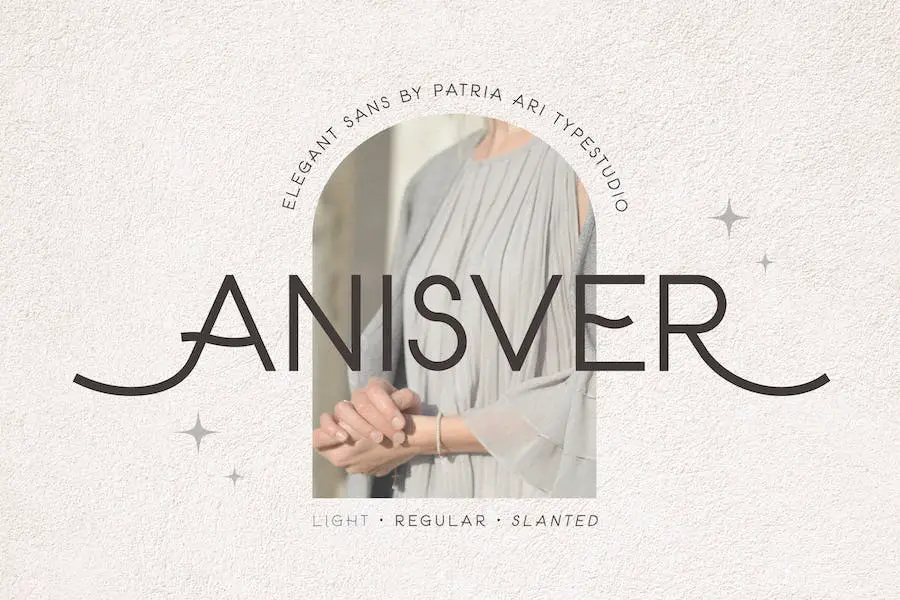
Anisver est une police sans empattement élégante qui apporte une touche de modernité et de simplicité à vos projets. Sa polyvalence vous permet de l'utiliser à diverses fins telles que des couvertures de magazines, des titres, des invitations de mariage, des logos et des conceptions de modèles PowerPoint.
Avec son design élégant et élégant, Anisver ajoute un aspect professionnel et soigné à votre travail. Que vous soyez un graphiste cherchant à améliorer vos projets ou un professionnel ayant besoin d'une police pour vos présentations, Anisver est un excellent choix.
Ses lignes épurées et son aspect contemporain feront ressortir vos créations et laisseront une impression durable. Alors pourquoi attendre ? Essayez Anisver aujourd'hui et élevez vos projets vers de nouveaux sommets.
Grand et petit
Tall & Tiny est un délicieux duo de polices qui apporte ludique et humour à vos créations. Avec son style unique fait à la main, cette police est parfaite pour créer des présentations amusantes, des invitations et une image de marque ludique.
En plus de la police principale, vous bénéficiez également de 52 extras dessinés à la main, comme des insectes, des fleurs, des lignes et des feuilles, pour améliorer encore davantage vos créations.
Avec Tall & Tiny, vous pouvez ajouter une touche de fantaisie et de légèreté à vos présentations PowerPoint. L'aspect distinctif de la police, fait à la main, donne à vos diapositives une ambiance amusante et ludique, les rendant plus attrayantes et mémorables pour votre public.
Ce duo de polices est non seulement idéal pour les présentations, mais également suffisamment polyvalent pour être utilisé dans divers projets de conception. Que vous créiez des invitations pour une fête d'enfants ou que vous conceviez un logo pour une marque originale, Tall & Tiny peut ajouter une dose supplémentaire de personnalité et de charme.
Géminienne
Geminy est une police moderne et élégante qui ajoute une touche de style céleste à vos créations. Cette police unique est parfaite pour les graphistes qui cherchent à rehausser leurs projets avec une touche de sophistication.
Avec Geminy, vous pouvez instantanément améliorer le design de vos présentations, créant une expérience visuelle professionnelle et accrocheuse pour votre public.
L’une des caractéristiques remarquables de Geminy est sa touche de style céleste. La police intègre des éléments inspirés du cosmos, donnant à vos créations une sensation captivante et éthérée.
Que vous travailliez sur une présentation PowerPoint, une affiche ou un site Web, Geminy apportera une touche de magie à votre projet.
Le design moderne et élégant de Geminy la distingue des autres polices. Ses lignes épurées et ses courbes élégantes en font un choix polyvalent pour un large éventail de projets.
Il dégage un sentiment de sophistication sans être trop autoritaire, permettant à votre contenu de briller tout en faisant impression.